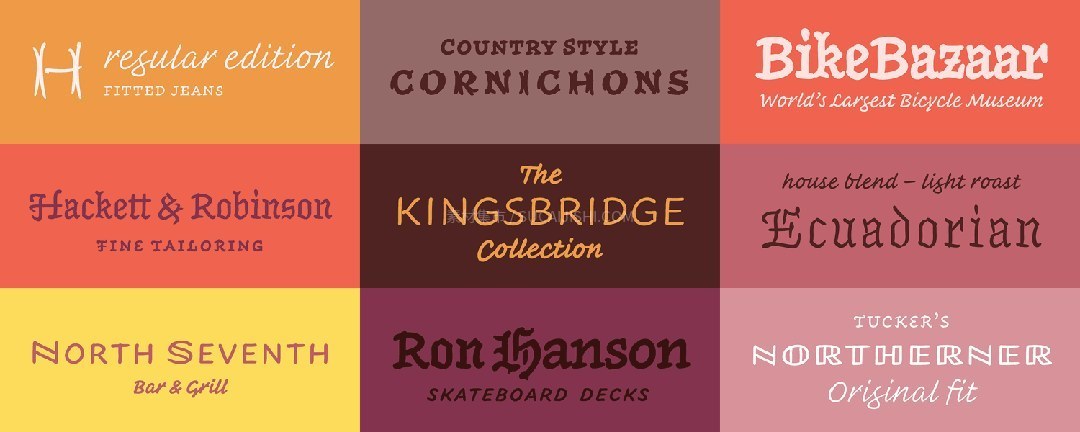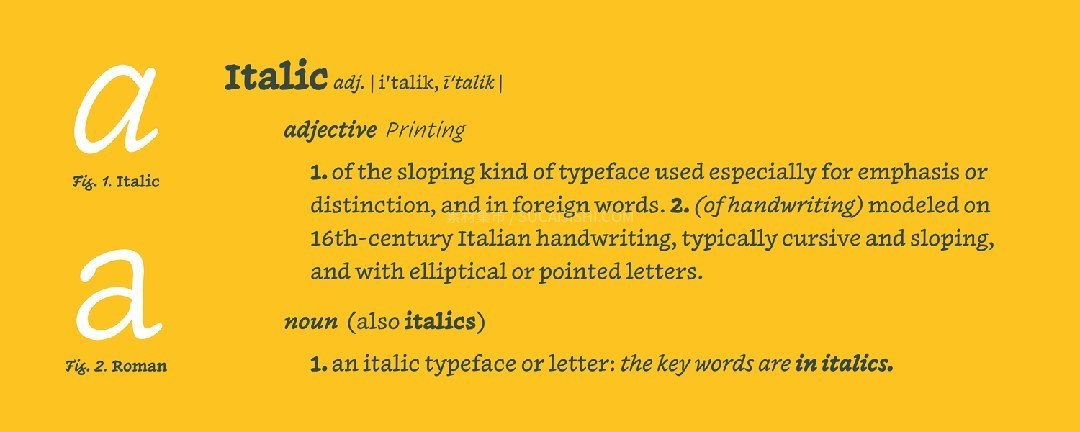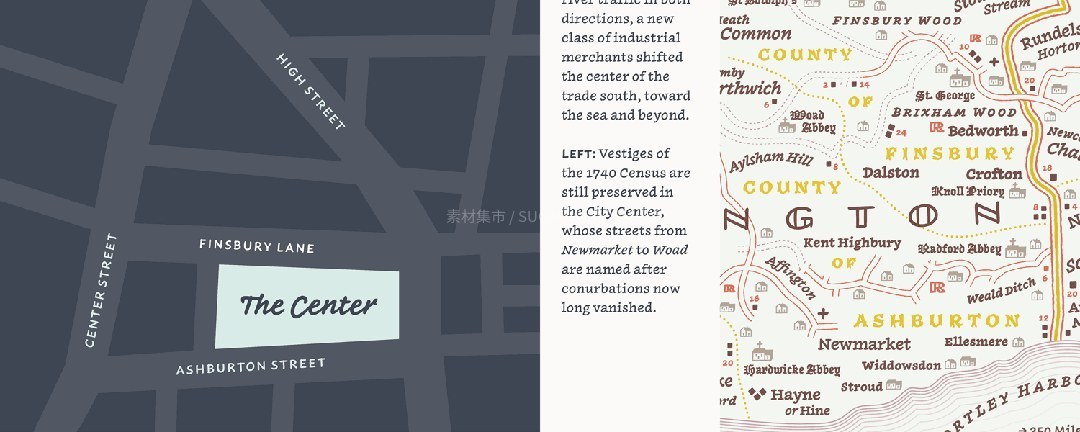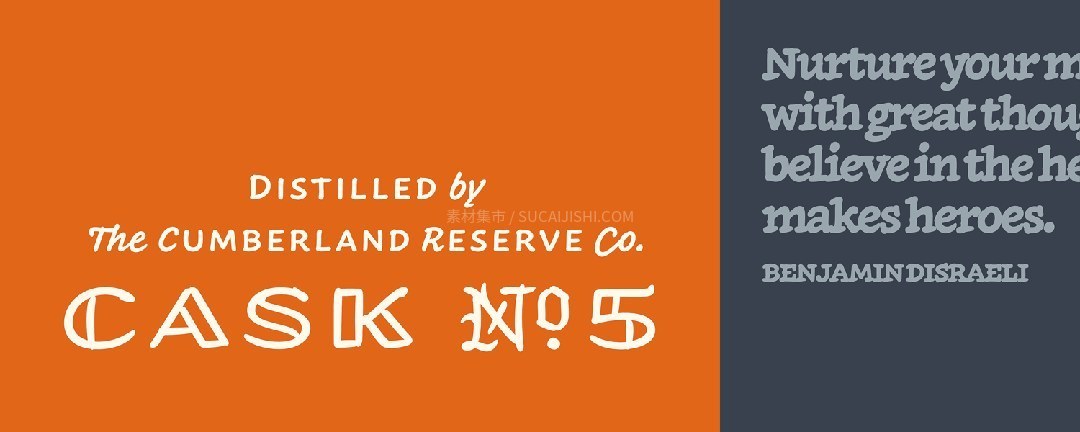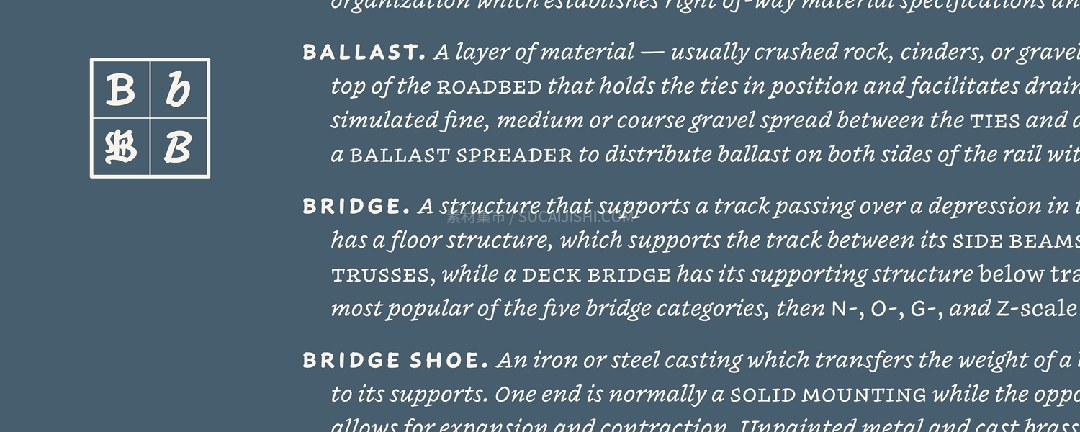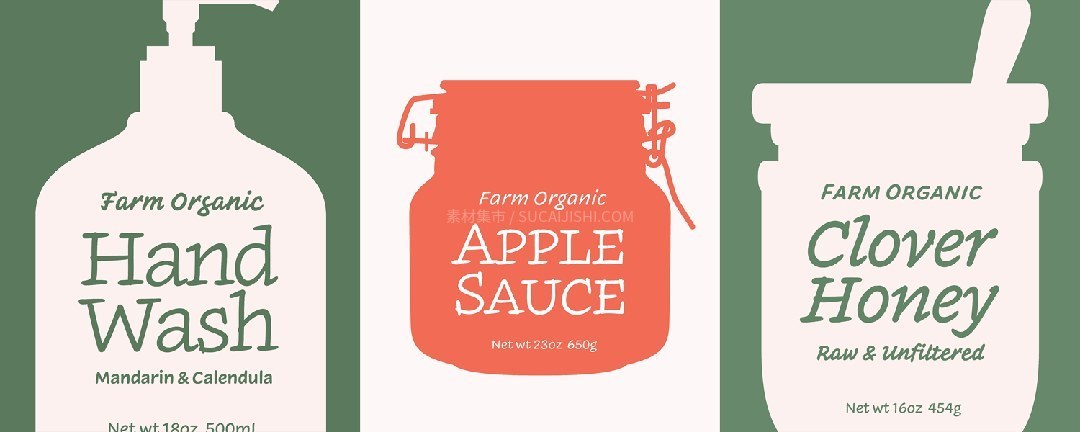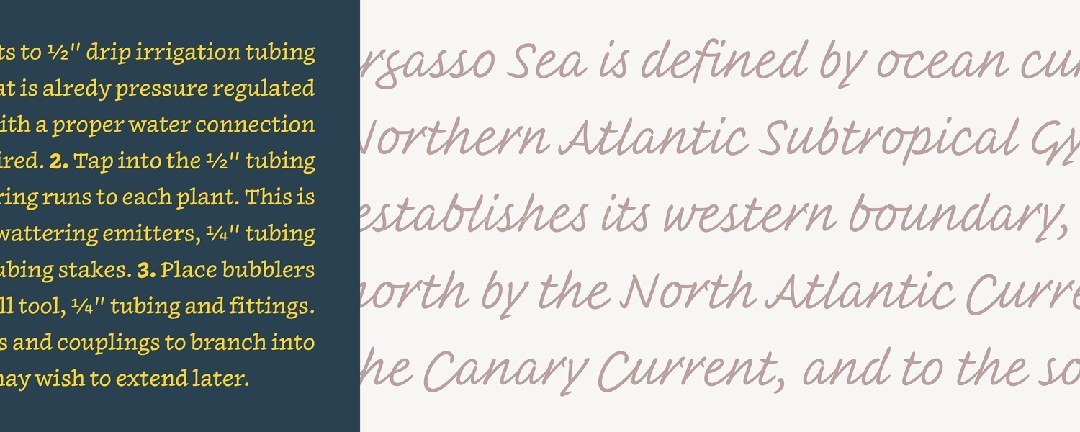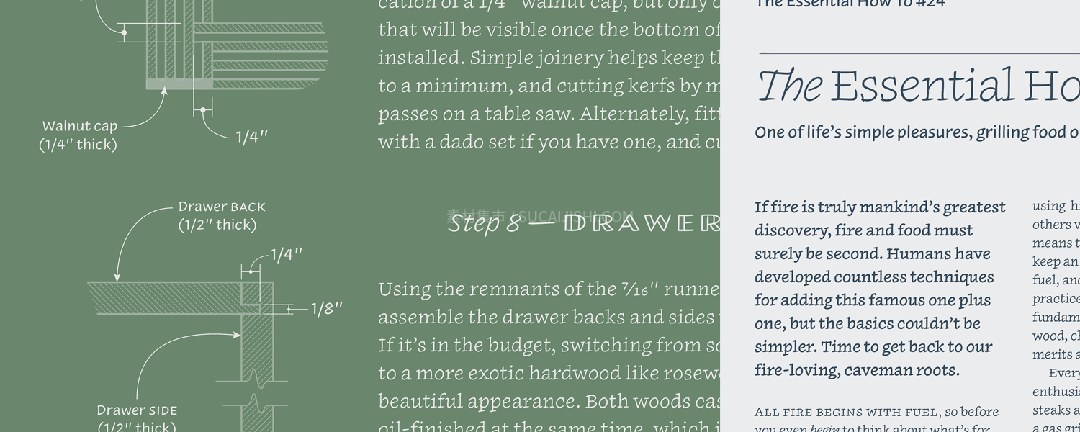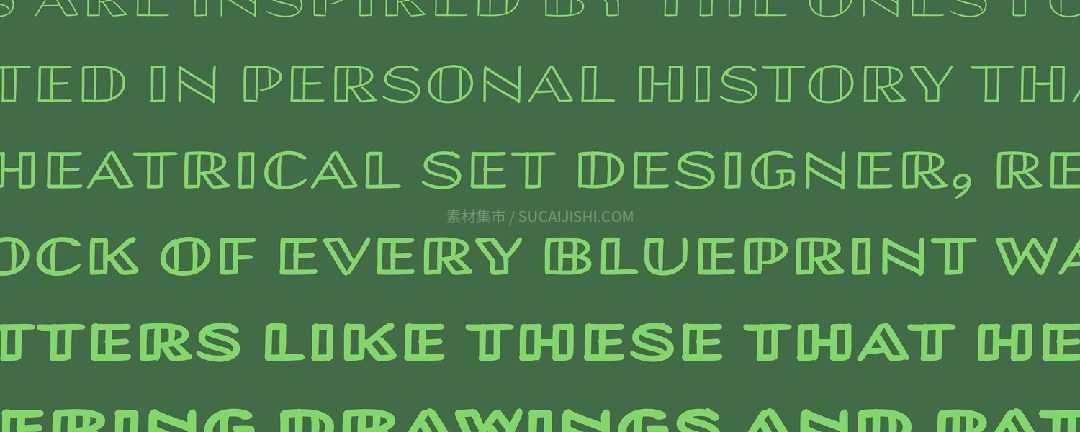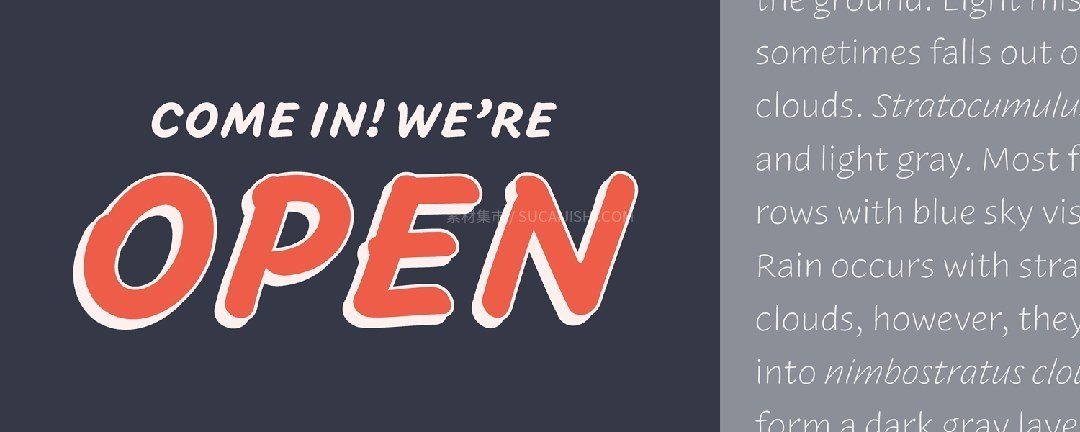
Inkwell多风格手写排版字体家族
Inkwell 是一款极具突破性的多风格手写感字体家族,包含 7 种字重、共计 54 种样式,涵盖黑体、紧缩体、开放无衬线体、手写体、衬线体和托斯卡纳体等多种风格。由 Jonathan Hoefler 设计的这套微型字体世界,完美融合了手写的随意性、字母的表现力和印刷体的多功能性。它是首款运用手写美学诠释多种排版风格的字体,打破了传统印刷字体的束缚感,让排版拥有如真实书写般无限的表达力与灵活性,为设计师提供了一个既严谨又充满个性的全能排版工具。